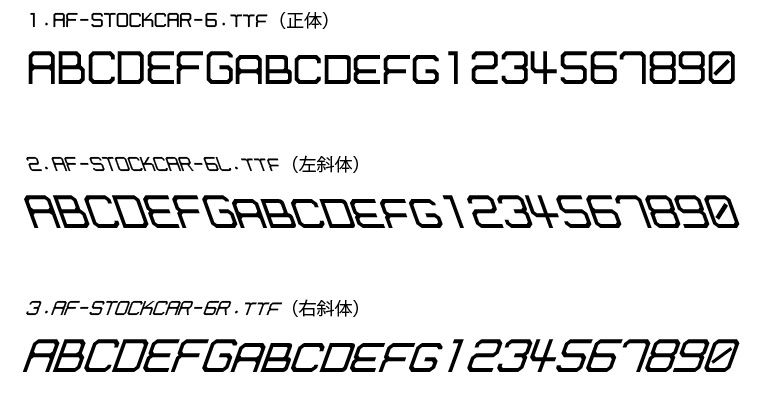
【収録書体】
本商品は下記3書体のセットです。
AF-STOCKCAR-6.ttf(正体)
AF-STOCKCAR-6L.ttf(左斜体)
AF-STOCKCAR-6R.ttf(右斜体)
※プレビューフォントは「AF-STOCKCAR-6.ttf(正体)」です。
アメリカのストックカーレーシングで使われるレースカー側面に貼られる数字や文字を模した1Byte欧文デザインフォントです。
AP機能の関わらず左右斜体が利用できる便利なセットです。